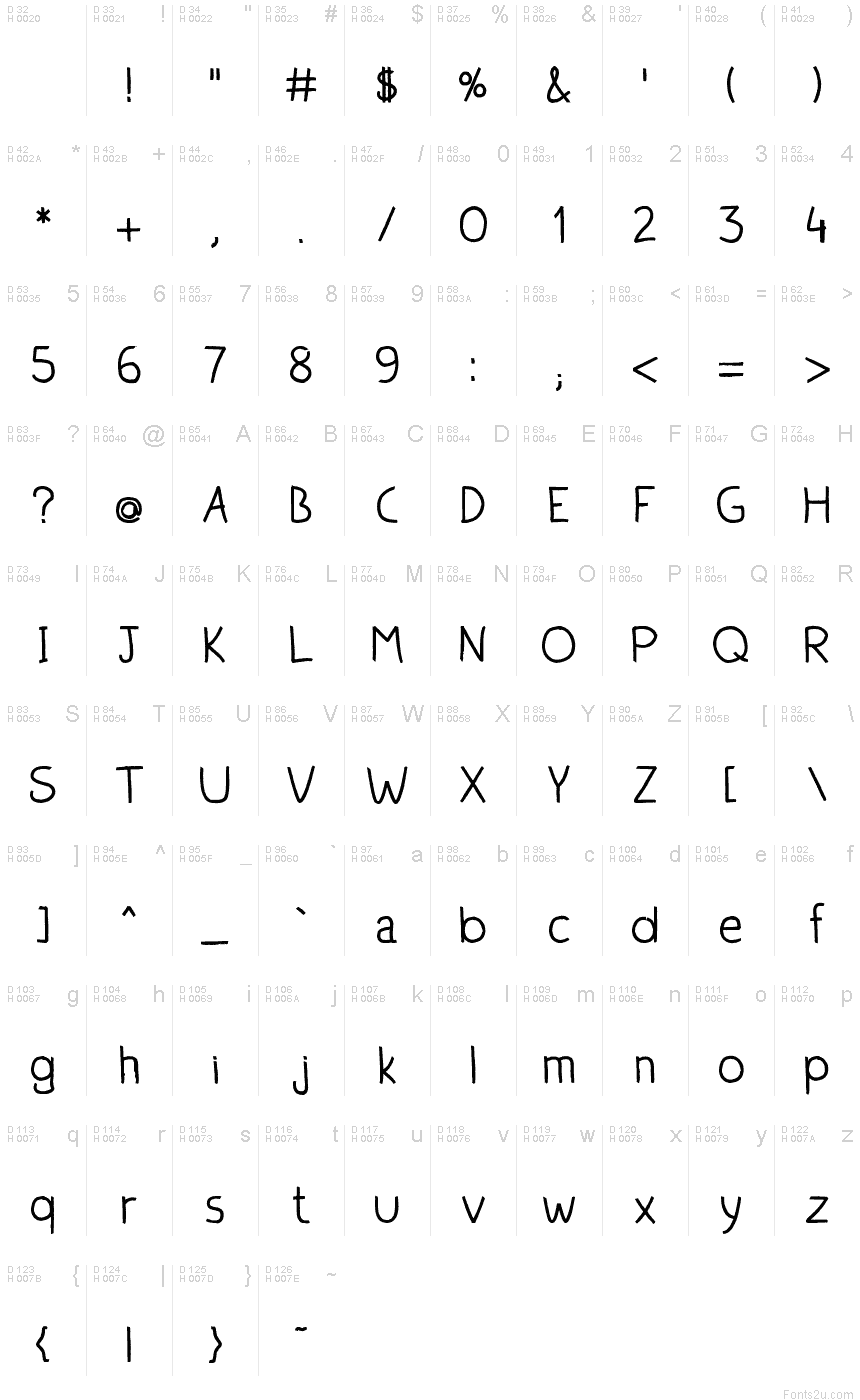
Quixeramobim Normal
A fonte Quixeramobim foi inspirada no nordeste do Cear, uma criao de Antnio Adriano em 30/11/2009.
The font Quixeramobim was inspired in northeastern Cear, a creation of Antonio Adriano on 30/11/2009.